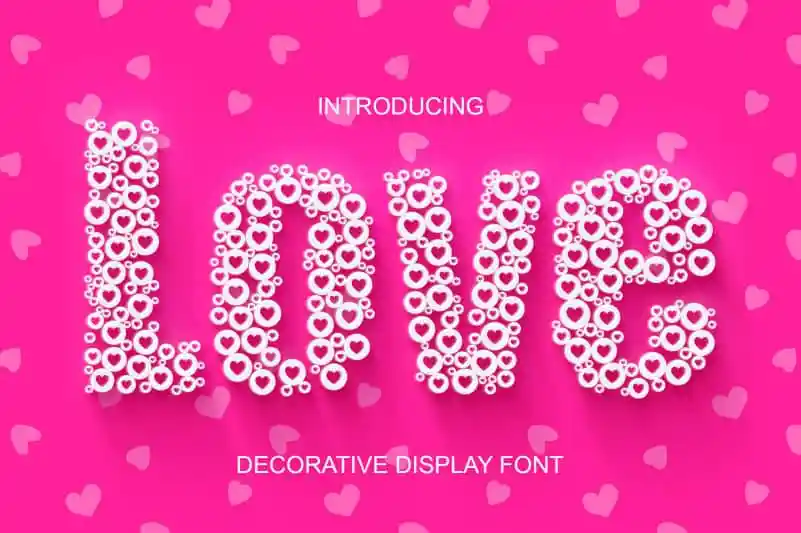
Esta é uma fofa fonte decorativa com tema do amor único. Ideal para qualquer projeto de design que precise de um aspecto encantador e delicado. Seja um card wedding, adesivo ou até mesmo como um toque romântico em um banner, ela faz o seu trabalho maravilhosamente bem. Perfecta para complementar seus projetos com uma pitada de amor, cada caractere diz “Love” em sua própria maneira única. Descubra por que esta fonte decorativa é tão amado e adorado entre os designers.